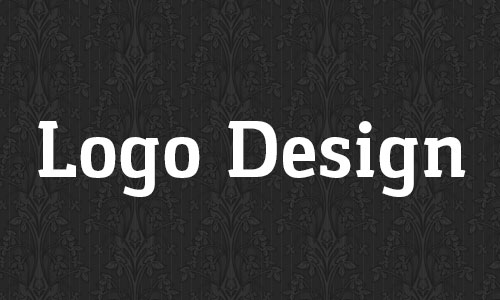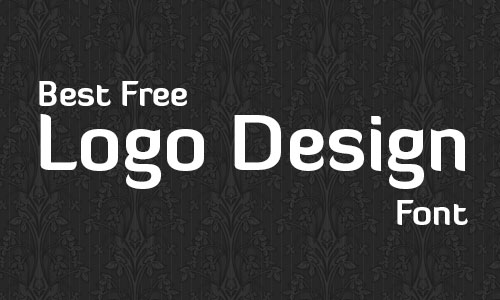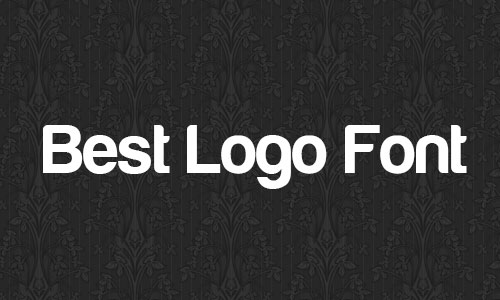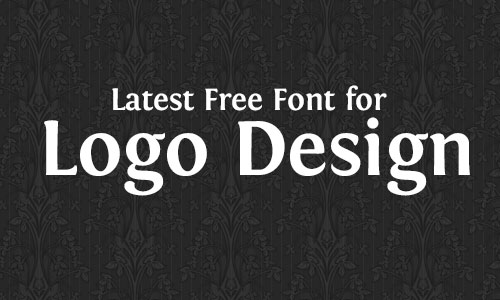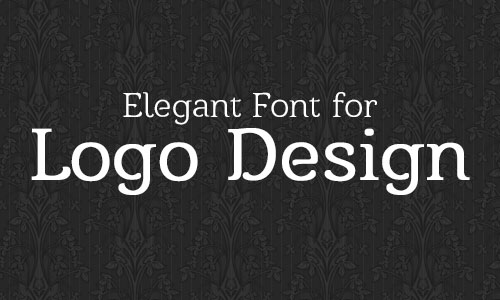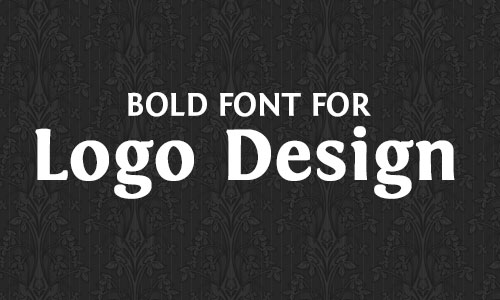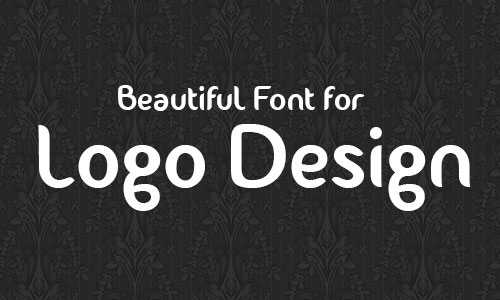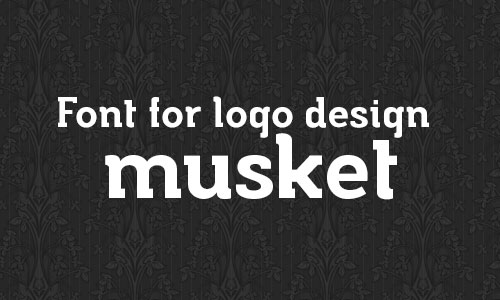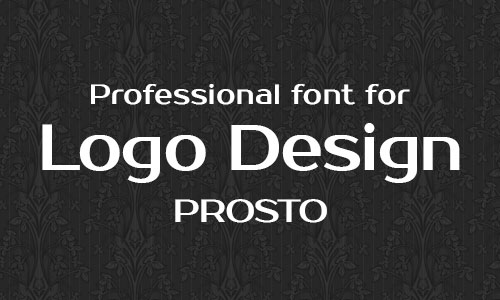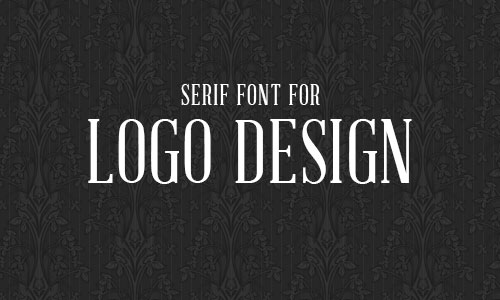
Tải miễn phí: 15 Font chữ cho thiết kế logo
Logo là đại diện của các công ty.Nó có một vai trò quan trọng trong việc tạo ấn tượng với khách hàng của công ty. Bản sắc và phong cách của một công ty được thể hiện ngay trên một thiết kế logo
Font chữ của logo cũng quan trọng không kém. Chọn font chữ luôn là sự khác biệt giữa các thiết kế logo. Tạo ra một logo cho các công ty lớn đòi hỏi font chữ phải thanh lịch. Bạn có thể tạo ra một phong cách của mình qua các font chữ. Các phông chữ không nên và mang một ý nghĩa lộn xộn, nên chọn những font có thể dễ đọc. Nói chung có ba loại phông chữ được sử dụng trong thiết kế logo :phông chữ Serif, Sans Serif và Script font.
Các phông chữ Serif không được sử dụng thường xuyên.Các phông chữ Sans Serif được sử dụng rộng rãi và được khuyến cáo nhất, chúng ta có thể nhìn thấy chúng trong các biểu tượng của Pepsi, Sony và của Apple,….Script được sử dụng thường xuyên, như chúng ta thấy nó trong thiết kế logo Coca-cola,người tiên phong trong sử dụng các font chữ.
Có rất nhiều phông chữ miễn phí mà bạn có thể tải về từ internet, nhưng không thích hợp cho thiết kế chuyên nghiệp. Tìm kiếm các phông chữ miễn phí tốt nhất có thể là một nhiệm vụ rất khó khăn, việc tìm kiếm các phông chữ chất lượng cao miễn phí có thể còn khó khăn hơn.
Bài này bao gồm một bộ sưu tập 15 phông chữ miễn phí tốt nhất, phù hợp cho thiết kế nhận diện thương hiệu. Tôi hy vọng các bạn sẽ thích bộ sưu tập các font chữ dưới đây và hãy tải ngay lập tức, sử dụng nó trong thiết kế logo để tạo ra những logo chuyên nghiệp hơn.
1. Gasper | Free Slab Serif font chữ cho thiết kế logo năm 2014
2. Diavlo | Best Free Stylish logo font
3. Harabara | Best free san serif logo font
4. Fontin | Recommended free logo design font
5. Barkentina | Elegant Free Font for Logo design
6. Fontin | Sans Bold free font for logo
7. Fontastique | Beautiful Free Font for Logo Design
8. Musket | Free logo font 2104
9. Prosto | Free professional font for logo design
10 Abraham Lincoln | Free Serif font for logo design
11. Aero Matics san serif font for logo
12. Maven Pro Free Thin Font for logo
13. Sansation | Free font for logo design & headings
14. Constance Rounded font for logo design
15. Modern font for logo design free